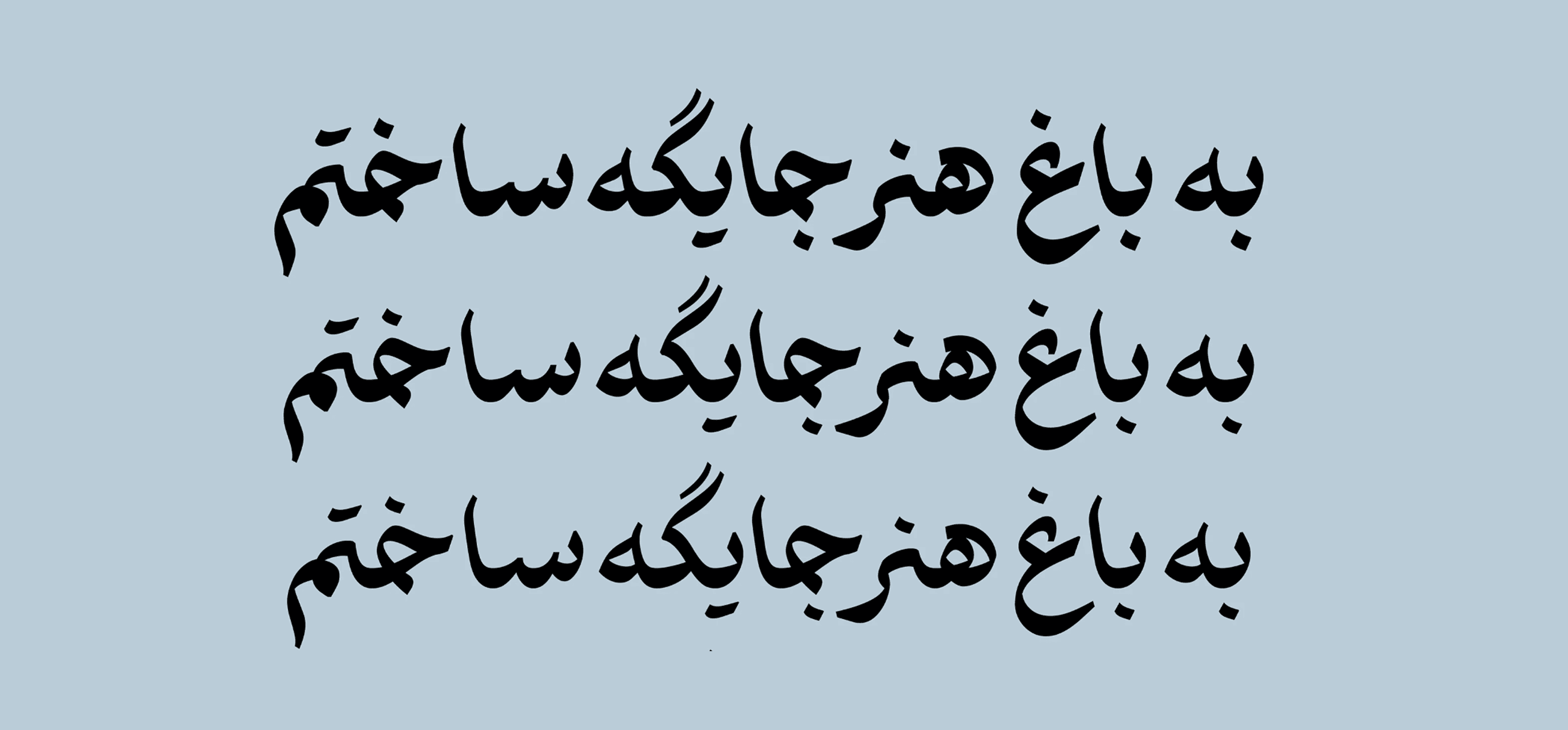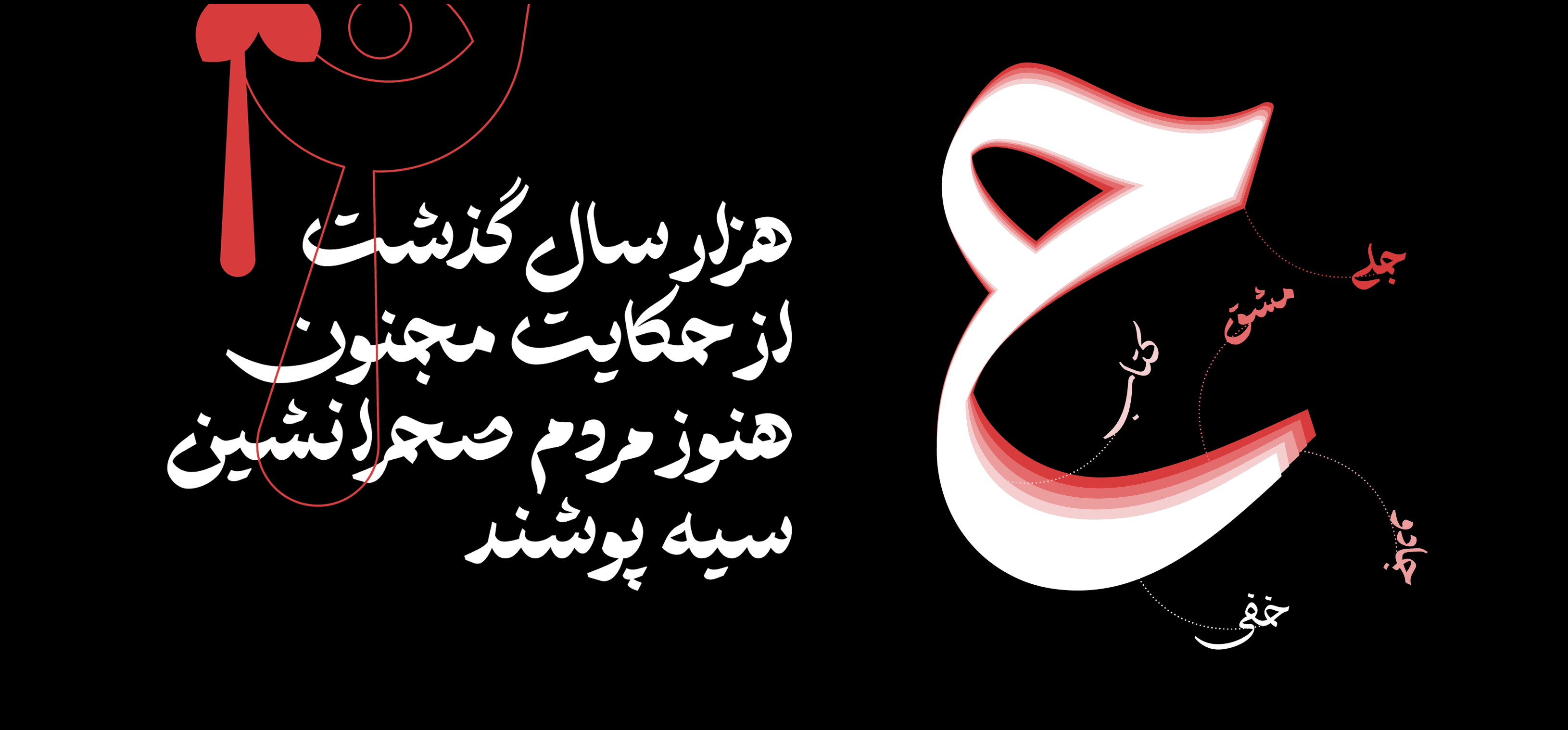
عائلة خطوط عرضية فارسية-عربية بتصميم معاصر جريء، تتميز بسمات زخرفية قوية وتكوينات حروف غير تقليدية.
يستوحي الخط عناصره من الفن الفارسي والزخارف النباتية، ليخلق مزيجًا بصريًا يعكس الحداثة والتراث في آن واحد.
مثالي للاستخدام في المشاريع الثقافية، الشعارات، الملصقات، والأعمال التي تتطلب تميزًا فنّيًا وحضورًا بصريًا لافتًا.